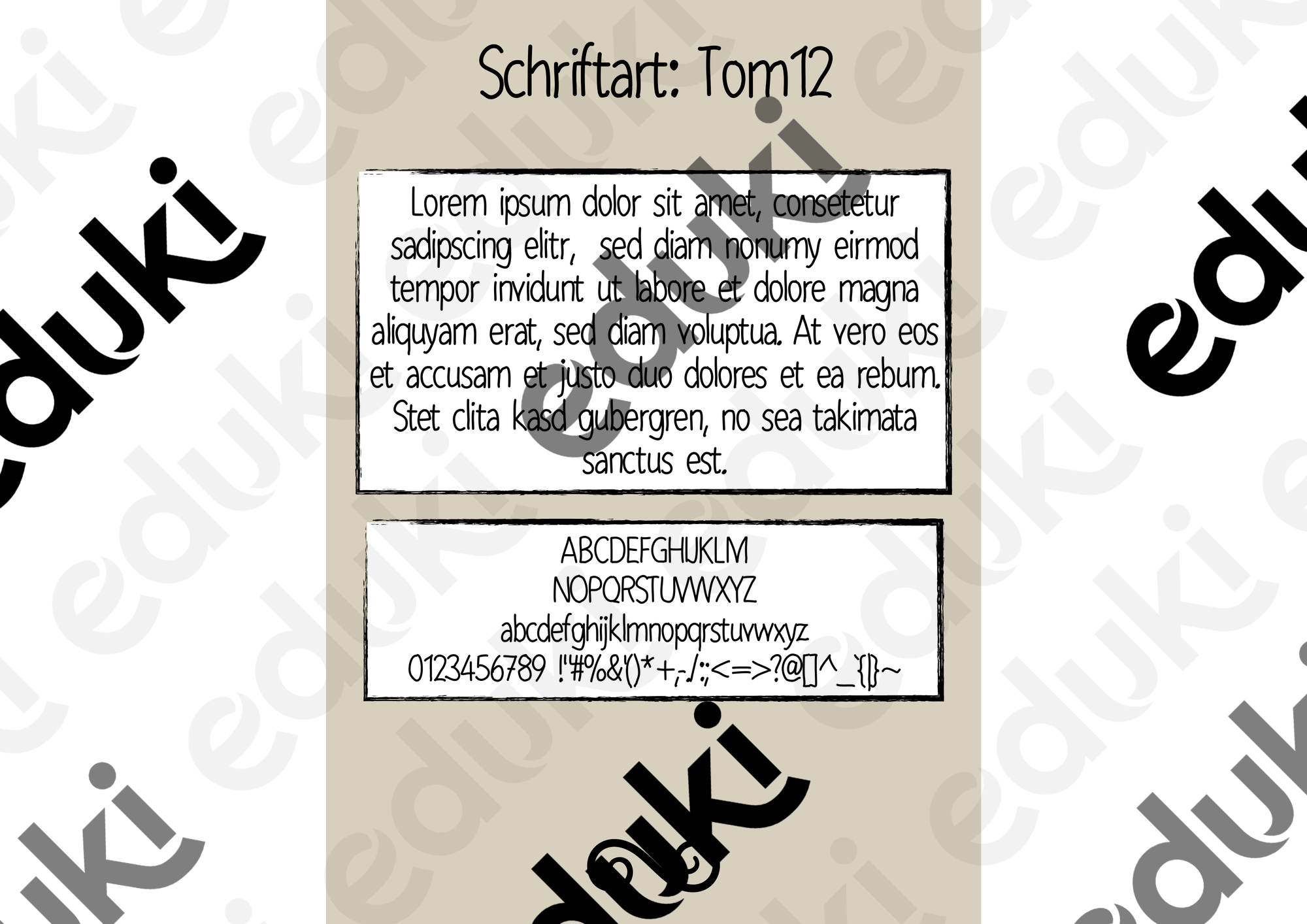
selbst erstellte Schriftarten - Schriftart: Tom12 (privat und kommerziell einsetzbar) - PLANTAGE - Deckblatt
Dies ist eine universell einsetzbare Schrift für viele Zwecke.
Schriftart: Tom12 (privat und kommerziell einsetzbar)